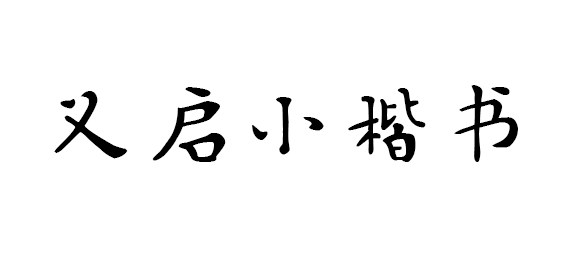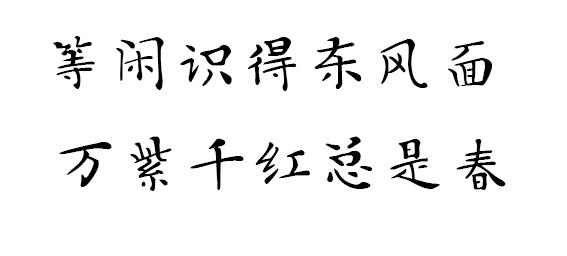
汉字演变总趋势由繁到简。汉字的形体从甲骨文到小篆、再从小篆到隶书、楷书。
小楷,即是楷体小字。 义启小楷书,是一款汲取历代小楷特质为基础的书法字库。而从现实效果上摆脱了书法字库在小显示屏上的弊端,主要在笔画上做了改善。小楷的灵魂在于“小字如大字 ”,就是字小要有大字的气象与章法。修饰笔画在保证气象的基础下,变的圆润简洁,不至于显示时出现不了效果反而糊掉。结构上收放有度,气势如虹。章法更是左右衔接,一气呵成。